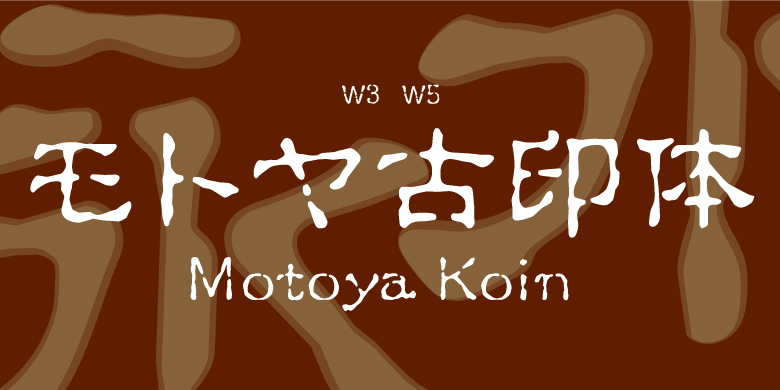
Motoya Koin
Motoya Koin,这款字体结构工整、笔画清晰,兼顾美观与易读性,适用于标题、正文、海报、包装、LOGO 等多种场景。字形优雅稳定,风格百搭耐看,适配日常排版与创意设计,让文字呈现更舒适、更具质感。Motoya Koin一笔一画,皆是细节,以均衡的比例、流畅的线条打造舒适视觉体验,字形端正大气,风格简约现代。无论是商业设计、品牌宣传还是日常排版,都能轻松驾驭,让文字更有格调与力量。Motoya Koin字体下载。
モトヤ古印体主要针对印章使用而设计,结合了优雅与力量,因而具有实用性。它适用于多种场合,如网站和游戏中的恐怖效果、各类商店的招牌、菜单、温泉旅馆的帘子,以及药品、糕点和调味料的包装设计等。